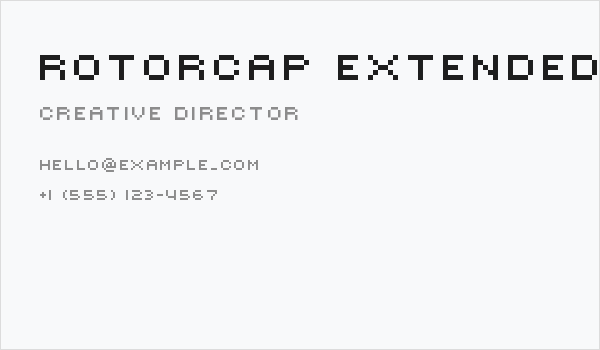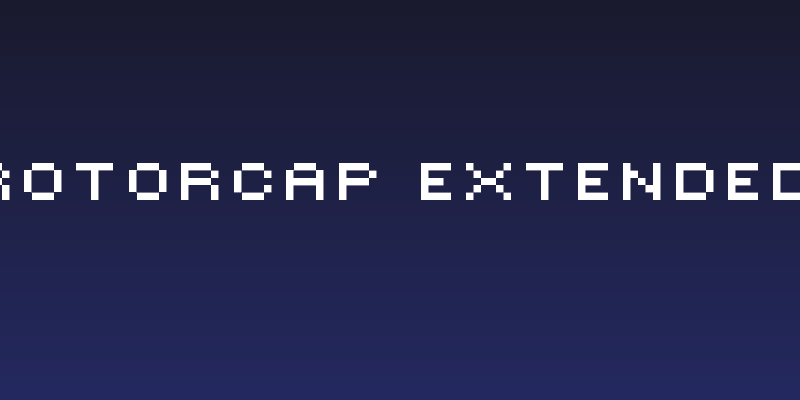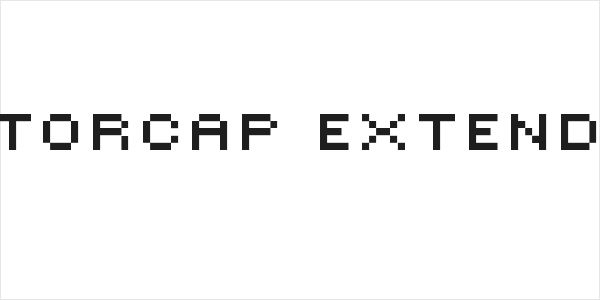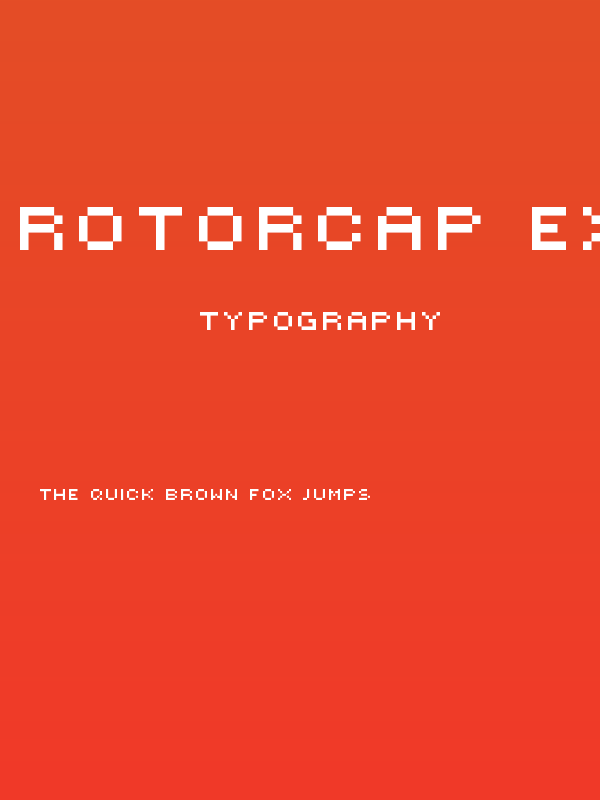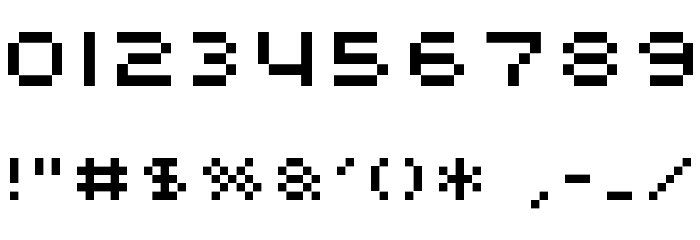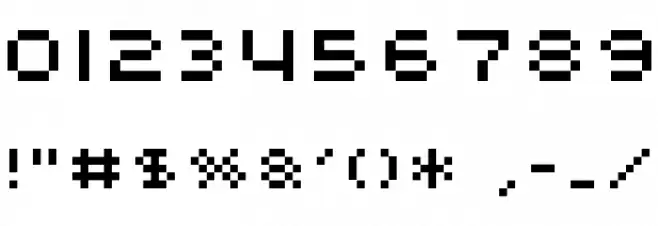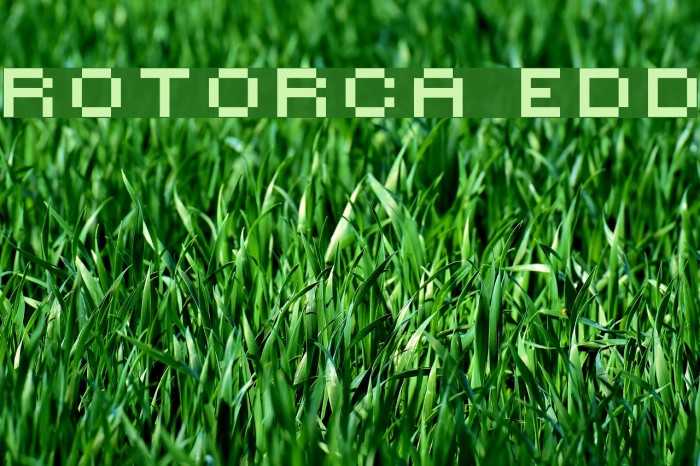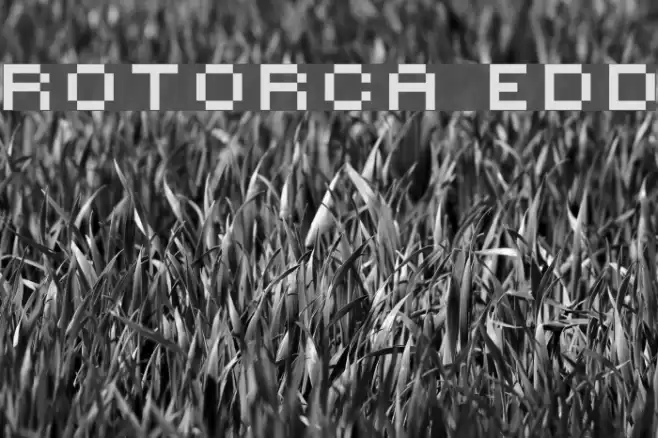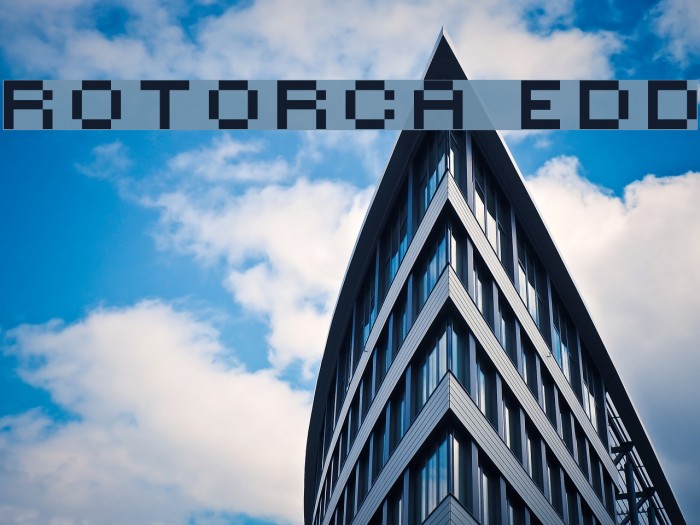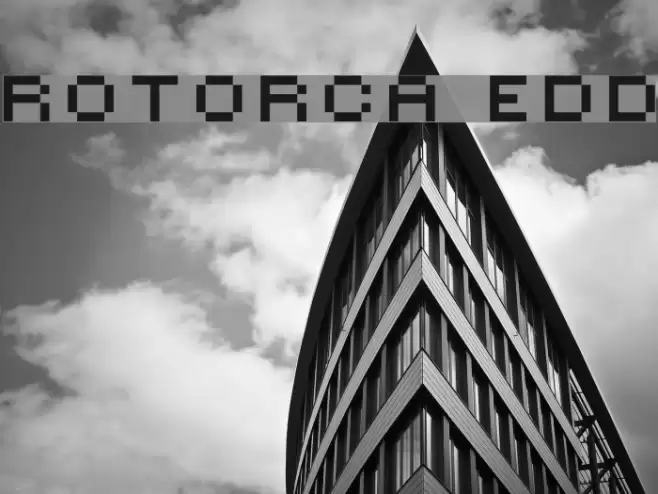
ROTORcap Extended Font
| Gesamtstil | Retro, Digital |
| Anwendungsfall | Headlines, Logos, Digital displays |
| Vorgeschlagene Projekte | Ideal for video game design, tech-themed posters, digital art, and retro-style branding. |